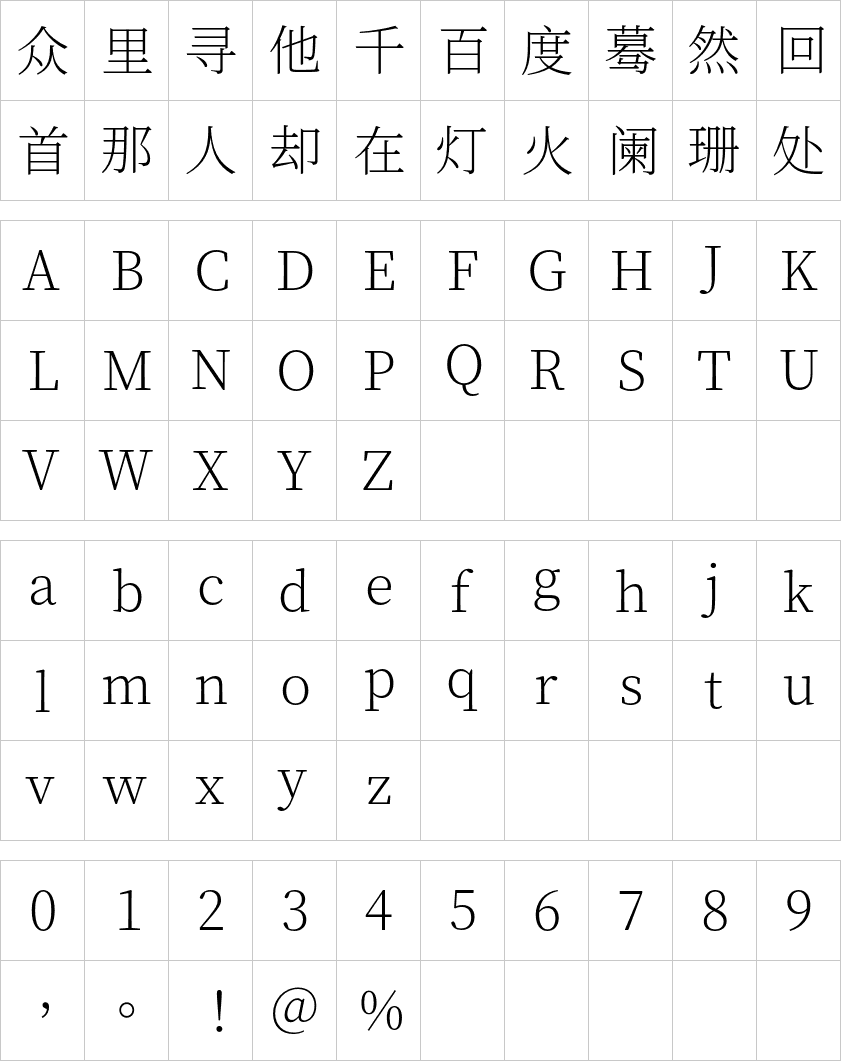
思源宋体ExtraLight
思源宋体(Noto Fonts) 是 Google 的一个开放原始码自由字型专桉,与 Adobe 公司合作,旨在提供一个可以涵盖 Unicode 全部字符的多语言、全方位字型,用「Noto」这名称来代表「No more Tofu(没有豆腐)」,试图消灭电脑中无法显示罕见文字时的那些空白方块(豆腐形状)。